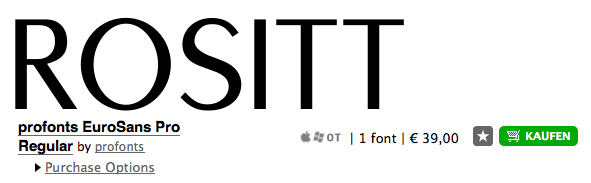
Kann mir bitte, bitte jemand sagen, welche Schrift das ist?
Die EuroSans geht in die Richtung …
SInd nicht auch die Strichstärkenunterschiede des O in der Vorlage größer? Oder täuscht das?
Da sind so einige Unterschiede zwischen der gesuchten Schrift und der EuroSans … drum schrieb ich: "Geht in die Richtung".